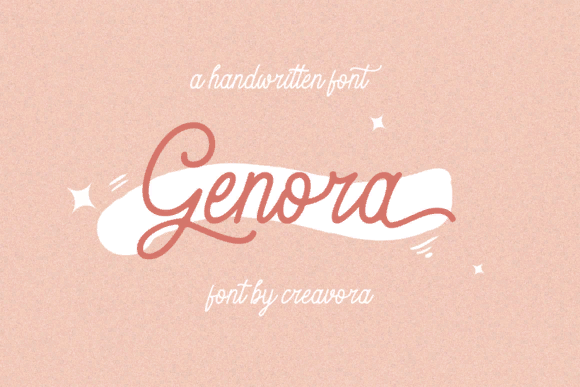
Название: Genora Font (2021)
Genora - это красивый и винтажный шрифт.
Он потрясающе смотрится на свадебных приглашениях, благодарственных открытках, цитатах, поздравительных открытках, логотипах, визитных карточках и любом другом дизайне, требующем индивидуального подхода.